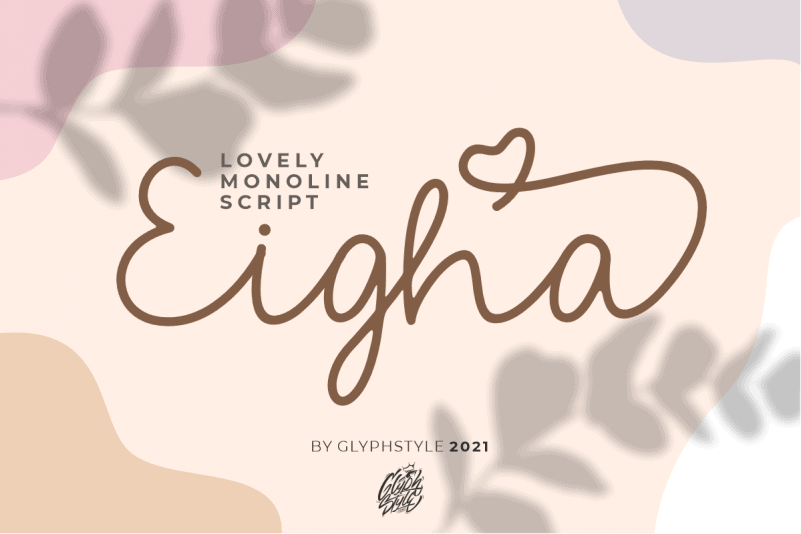
Eigha Script Font – Fonte Grátis
Eigha Script Font
Eigha Script Font é uma fonte script monoline que representa a delicadeza de uma escrita romântica à moda nova. Ideal para aplicações variadas como capas, marcas d’água, logomarcas, nomes e cartões de visitas, esta fonte traz uma arquitetura elegante e sofisticada. Suas linhas suaves e delicadas se tornam perfeitas para expressar um sentimento romântico em qualquer tipo de projeto visual. Eigha Script é uma escolha ideal tanto para designers gráficos quanto para aqueles que desejam criar elementos personalizados ou originais para seus projetos digitais e físicos.